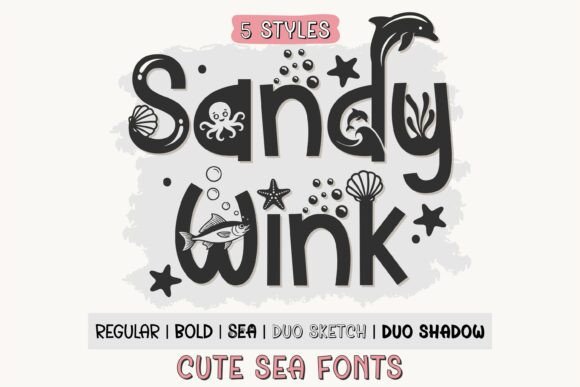
Sandy Wink Sea
適切なデザイン要素を見つけるのは難しい場合がありますが、Sandy Wink Seaは作品を即座に引き立てる優れたコレクションを提供します。
POD(オンデマンド印刷)製品、結婚式の招待状、またはソーシャルメディアのグラフィックを作成している場合でも、Sandy Wink Seaは理想的です。